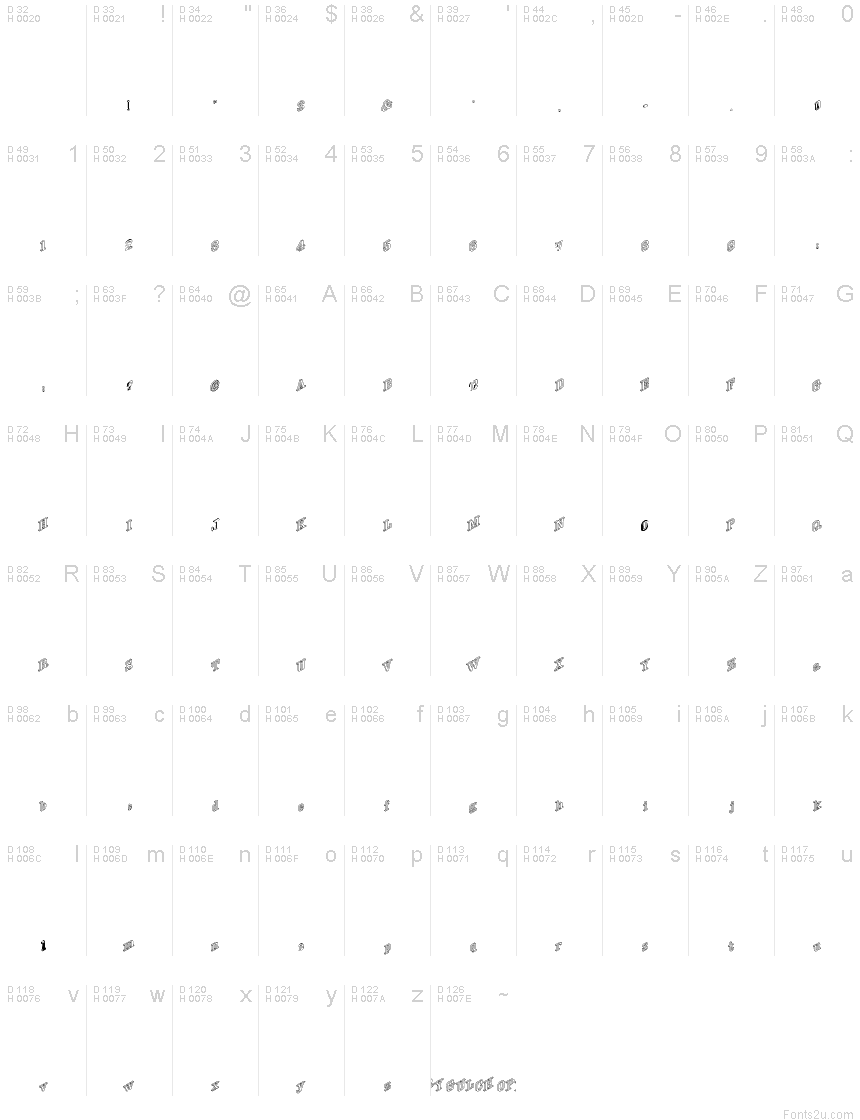
يعتبر خط Dry Gulch Open، الذي صممه J.F.Y. Daniel Gauthier من Gaut Fonts، خط عرض (display font) مجانياً ثلاثي الأبعاد مستوحى من طراز الويسترن، ويحمل في طياته سحر لافتات الحدود القديمة. تمزج الحروف بين خطوط slab serif ذات الزوايا، والوصلات المنحنية، والظلال البارزة المفتوحة، مما يضفي على التصميم لمسة هوائية وزخرفية بعيداً عن الثقل.
يصلح هذا الخط للملصقات، والعلامات التجارية ذات طابع الصالونات القديمة (saloon)، ومنشورات الفعاليات، وتصاميم الأغلفة، وعناوين النصوص، والشعارات القصيرة حيث يمكن لهذا المظهر البارز المرسوم يدوياً أن يترك أثراً. وباعتباره خطاً مجانياً، فهو مناسب أيضاً للحروف الاستهلالية والرموز (monograms)، لأن الخطوط الخارجية المشطوفة والمنحنيات الحيوية تمنح حتى بضعة حروف حضوراً كافياً لإثراء أي تصميم.
DryGulchOpen by J.F.Y.Daniel Gauthier - GautFonts